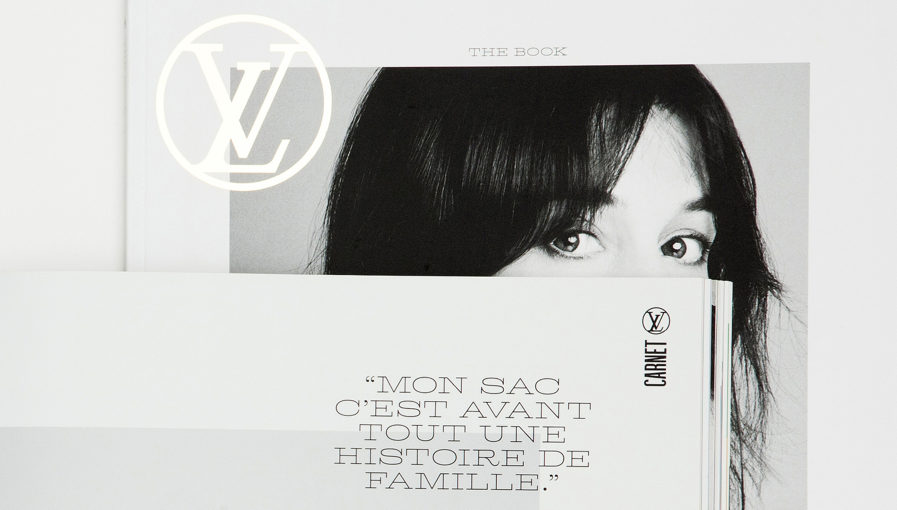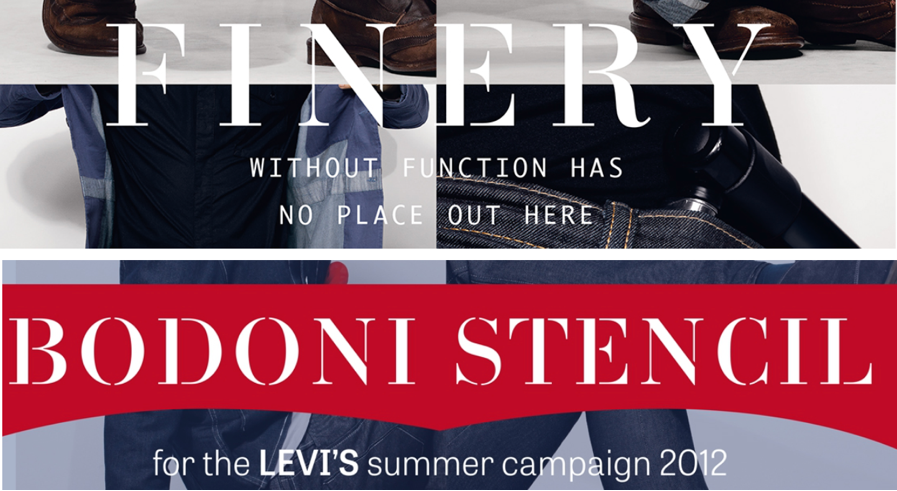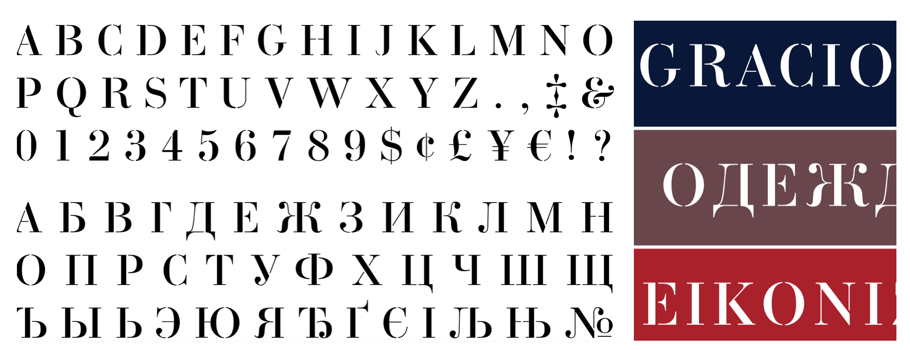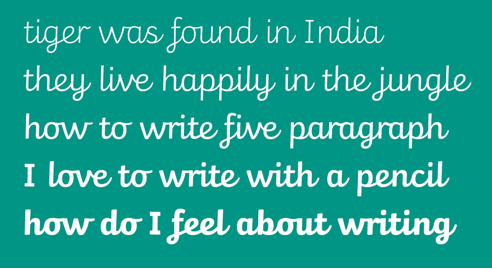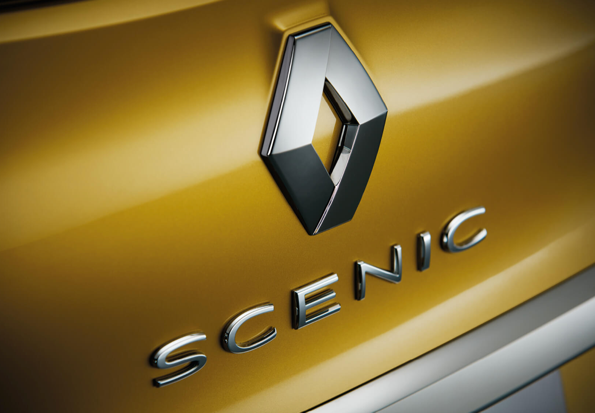
我们与专业的西文指导团队Typetogether,Monotype,Production Type合作,定制专业的西文字体
Apple Inc.
苹果公司的排版部门要求Typetogether设计团队研究一个全新的定制的字体以全面翻新iBooks图书应用程序。 Apple需要一种新的字体,以便在运行不同渲染技术的各种设备和高分辨率屏幕上提供出色的阅读体验。定制版Athelas应运而生,同时Athelas支持不同语言的词典、学术期刊和出版物。
LEVI'S
Typetogether为李维斯设计的定制字体
Twinkl Ltd.
Renault Vehicles
Production Type为雷诺汽车设计了一套品牌字体。车标设计不仅仅是字形的设计,而是需要考虑光线的衍射。因为车标反射的不是地面,而是天空。 许多设计思维都围绕着如何在生产制造中减少字母失真的方法。但大多数生产线的技术是不够的。光的柔和柔和的梯度无法实现,会产生锯齿状。解决办法是使用斜线曲线,一种在公路、铁路、过山车和汽车零件中流行的曲线。
Louis Vuitton Magazine
Production Type路易威登杂志设计的定制字体LV Clémence 满足了路易威登的品牌要求,同时在出版物光滑的涂层纸上提供清晰的标题。